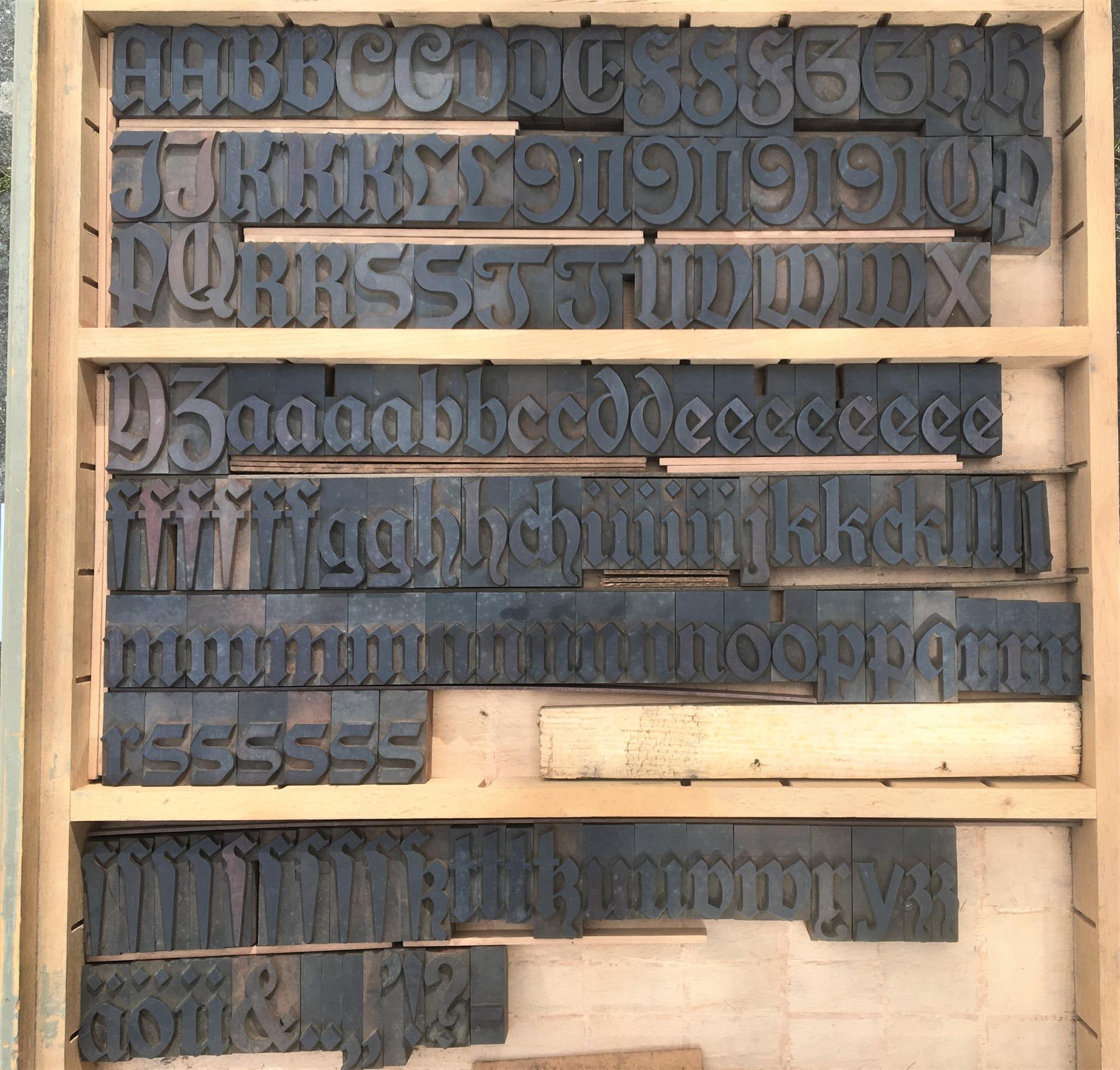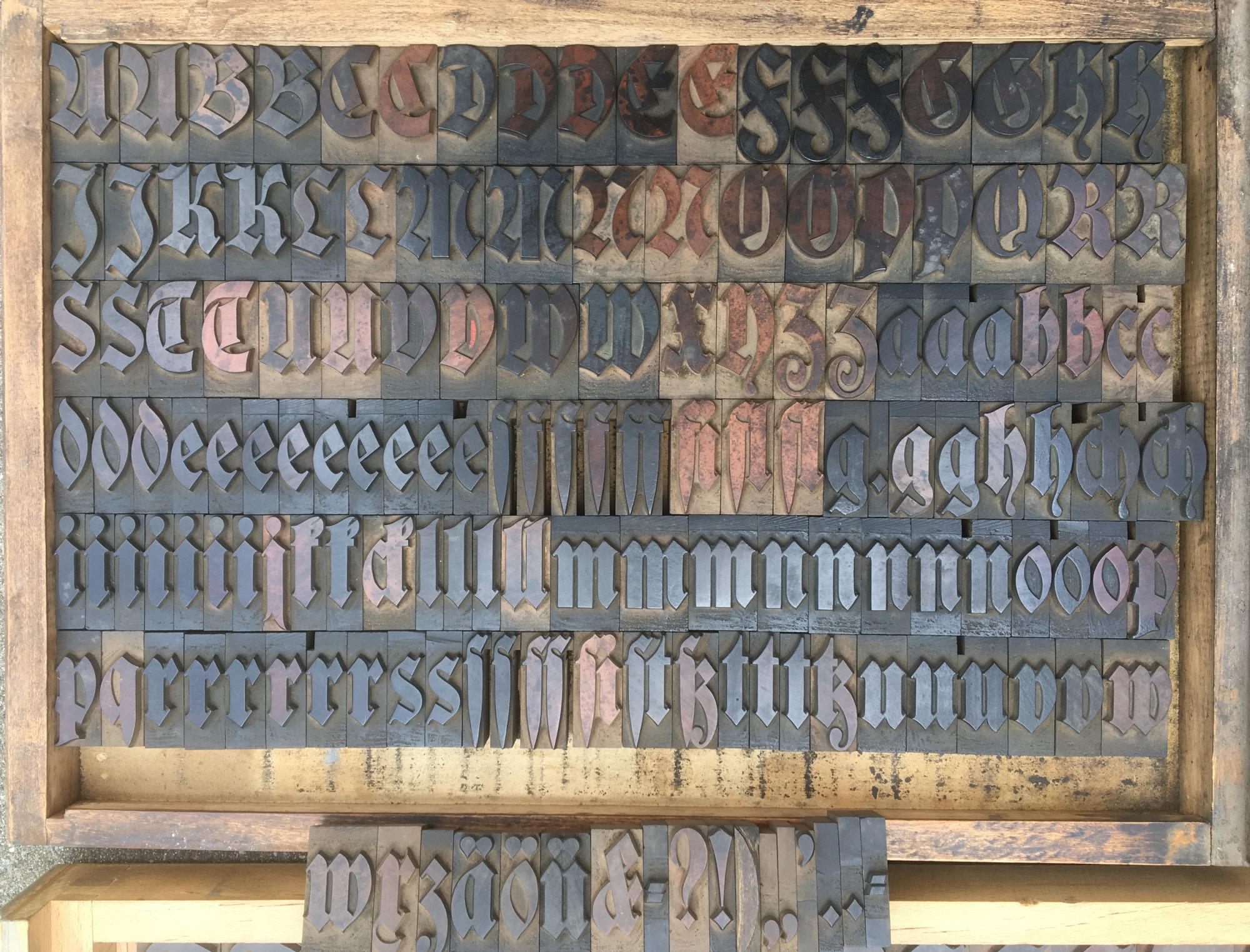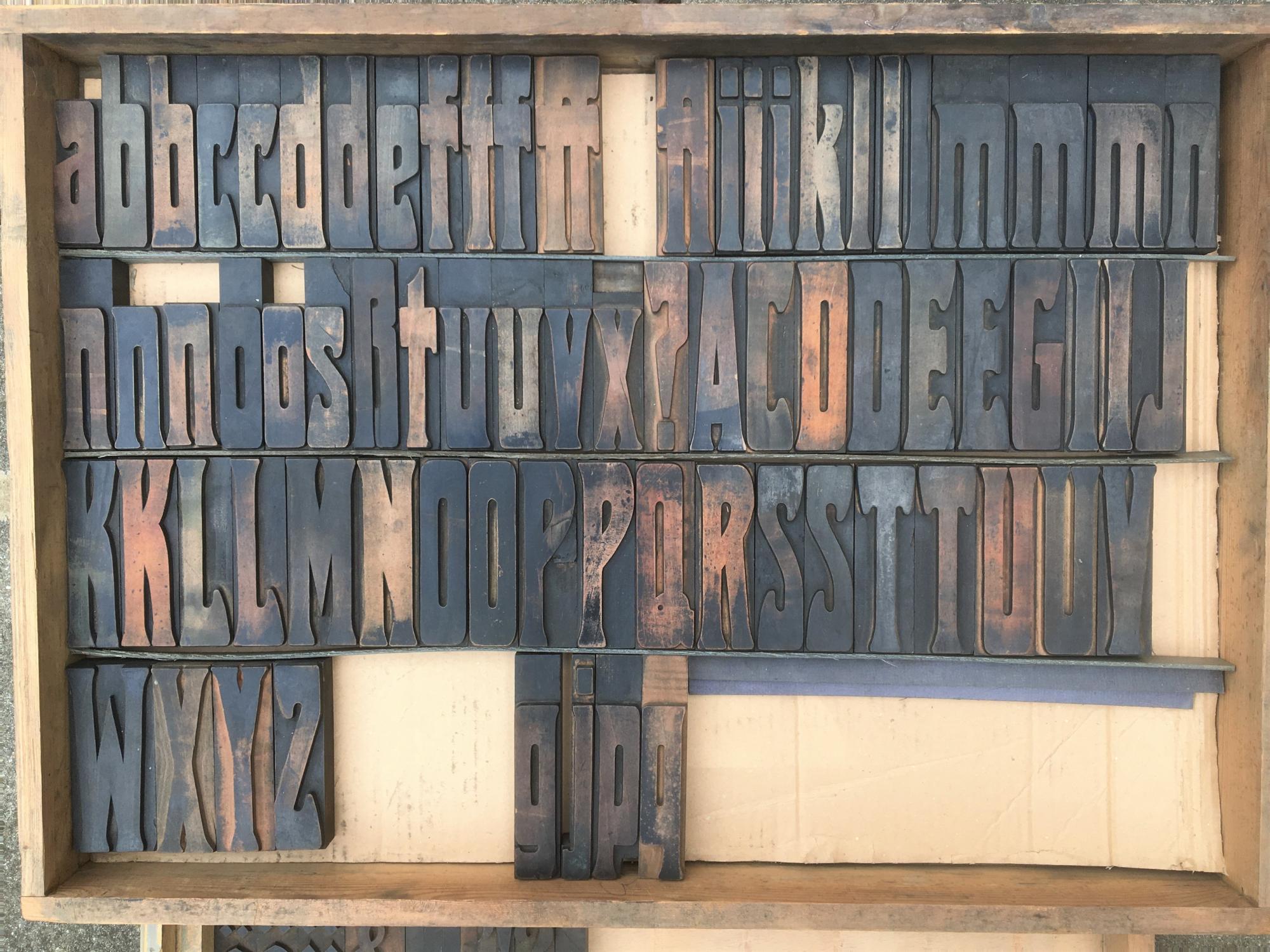
Identifikation von Holzlettern
unsere Plakatschriftensammlung hat diese Woche Zuwachs bekommen. Die Jugendstil-Schrift ist leider ziemlich unvollständig weshalb wir nach Hinweisen zum Originalnamen und evtl. einem kompletten Muster suchen. Die fehlenden "Figuren" sollen entweder in Holz oder Linol nachgeschnitten werden. Erfolglos durchsucht wurden bereits der Übergangskatalog "Sachs und Co./Roman Scherer AG ca. 1914", "Schelter & Giesecke 1928" und "Krebs Nachfolger, Die Auslese 1925".
Die beiden gebrochenen Schriften, die für ihr vermutliches Alter noch relativ vollständig sind, dürften schwieriger zu identifizieren sein. Geschnitten evtl. zwischen 1880 und 1920 wobei der Zustand des Holzes eher auf eine spätere Herstellung hinweist. Für jede Hilfe sind wir dankbar.